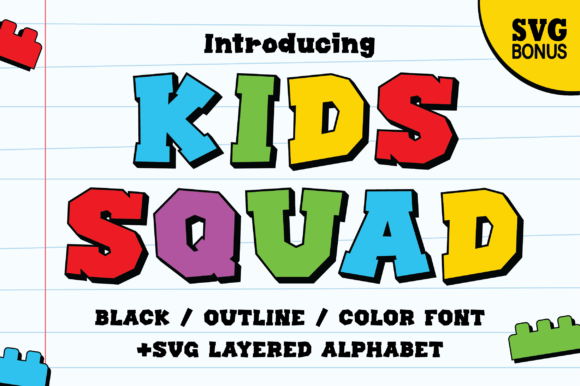
Kids Squad Font
Kids Squad Font – الخط المثالي لتصاميم الأطفال!
أضف لمسة من المرح والإبداع إلى مشاريعك مع Kids Squad Font، خط فريد مستوحى من عالم الأطفال المليء بالحيوية والألوان. يتميز هذا الخط بتصميم مرح وسلس يجعله مثاليًا لاستخدامات متنوعة مثل:
✅ تصاميم الشعارات والعلامات التجارية الخاصة بالأطفال
✅ أغلفة الكتب والقصص المصورة
✅ ملصقات وأدوات تعليمية تفاعلية
✅ دعوات أعياد الميلاد والمناسبات الخاصة
✅ تطبيقات وألعاب الأطفال